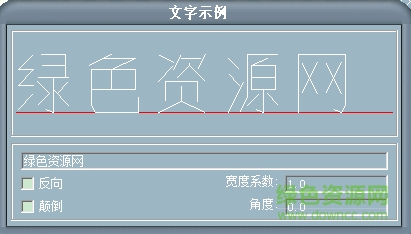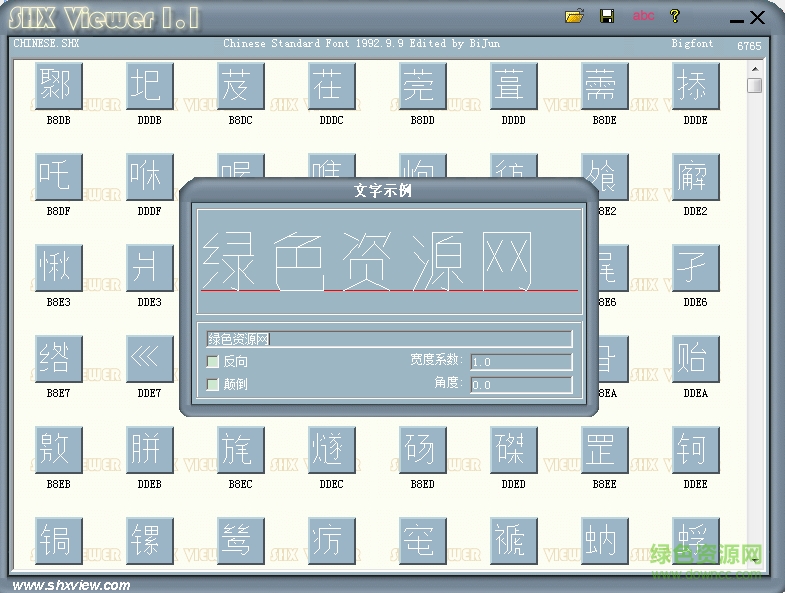
chinese.shx是一款常用的cad字體,這款字體筆畫纖細(xì),整體效果非常不錯(cuò),小編為您帶來chinese.shx免費(fèi)字體下載,歡迎來綠色資源網(wǎng)下載體驗(yàn)!
shx文件在CAD里叫形文件,它分為兩種:字體文件和符號(hào)形文件;字體文件又分兩種,可以叫做小字體和大字體。
小字體里面只包含一些單字節(jié)(在輸入法里稱為半角)的數(shù)字、字母和符號(hào) ,在文字樣式的左側(cè)列表中列出的都是小字體文件,如果文字樣式要使用CAD字體,首先必須選擇一種小字體。
大字體是針對(duì)中文、韓文、日文等雙字節(jié)(全角)文字定制的字體文件。 在文字樣式對(duì)話框中必須勾選“ 使用大字體 ”,才能在右側(cè)列表中選擇大字體文件。由于中文、日文的字符比較多,而且每個(gè)字符的定義都比較復(fù)雜,這類文件通常比較大,從幾百K到幾MB不等。